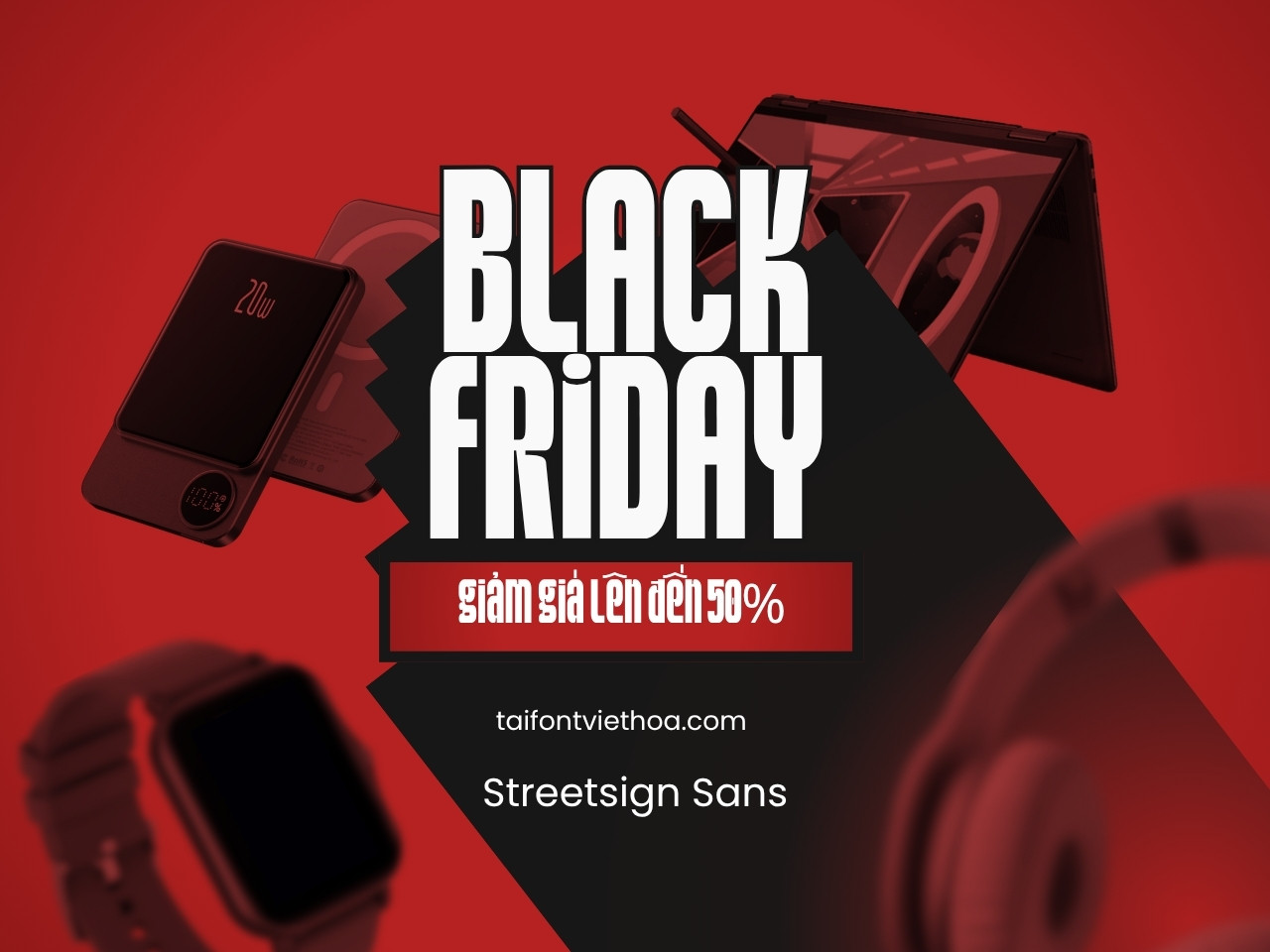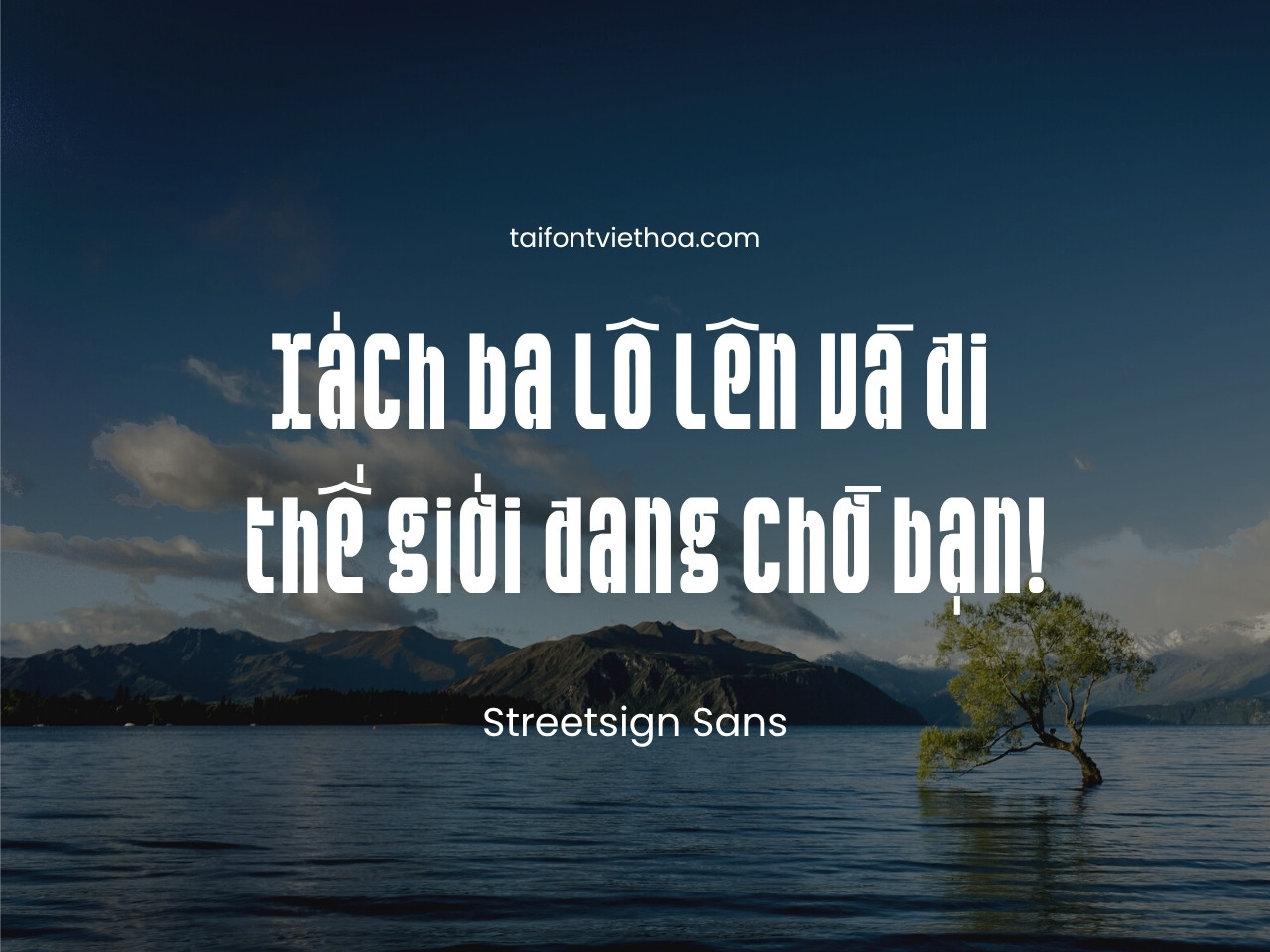
Giới thiệu về font Streetsign Sans – phong cách bảng chỉ đường đương đại
Streetsign Sans là một thiết kế sans-serif hiện đại được lấy cảm hứng từ các bảng chỉ dẫn giao thông, biển báo và hệ thống định hướng trong không gian đô thị. Bản gốc được phát triển bởi Harry Dinh – một nhà thiết kế font Việt Nam, người đã khéo léo kết hợp giữa tính ứng dụng cao và tính thẩm mỹ trong từng đường nét. Font được thiết kế nhằm tối ưu cho khả năng đọc nhanh, rõ ràng trên mọi kích thước, từ bảng hiệu lớn ngoài trời đến giao diện kỹ thuật số nhỏ gọn.
Phiên bản tiếng Việt được chính tác giả Việt hóa hoàn chỉnh, đảm bảo tương thích hoàn toàn với bảng mã Unicode và hỗ trợ đầy đủ các dấu tiếng Việt. Bên cạnh đó, Streetsign Sans còn hỗ trợ hơn 80 ngôn ngữ dùng bảng chữ cái Latin, giúp ứng dụng được trong nhiều ngữ cảnh toàn cầu. Font này đã được taifontviethoa.com sưu tầm, chọn lọc kỹ lưỡng và chia sẻ đến cộng đồng thiết kế Việt với mong muốn giúp các dự án quảng cáo, định hướng thương hiệu và hệ thống nhận diện được truyền tải hiệu quả hơn.
Đặc điểm hình khối rõ ràng – Tối ưu hiển thị nhanh
Streetsign Sans sở hữu cấu trúc sans-serif với đường nét cứng cáp, các ký tự vuông vức, khoảng cách chữ rộng vừa phải, giúp tăng khả năng nhận diện chữ cái từ xa. Độ dày đều, không có độ tương phản phức tạp nên đặc biệt dễ đọc ở mọi kích thước. Một số biến thể trong bộ font cho phép mở rộng thiết kế cho các biển báo, tiêu đề mạnh mẽ hoặc giao diện công nghệ.
Font này lý tưởng cho các ứng dụng liên quan đến giao thông, bản đồ, giao diện điều hướng UI/UX, bảng hiệu, hệ thống thông tin công cộng, các chiến dịch quảng cáo ngoài trời và lĩnh vực công nghệ. Ngoài ra, các ngành như bất động sản, truyền thông, logistics, hoặc thiết kế sự kiện cũng có thể khai thác hiệu quả tính linh hoạt và rõ ràng của Streetsign Sans.